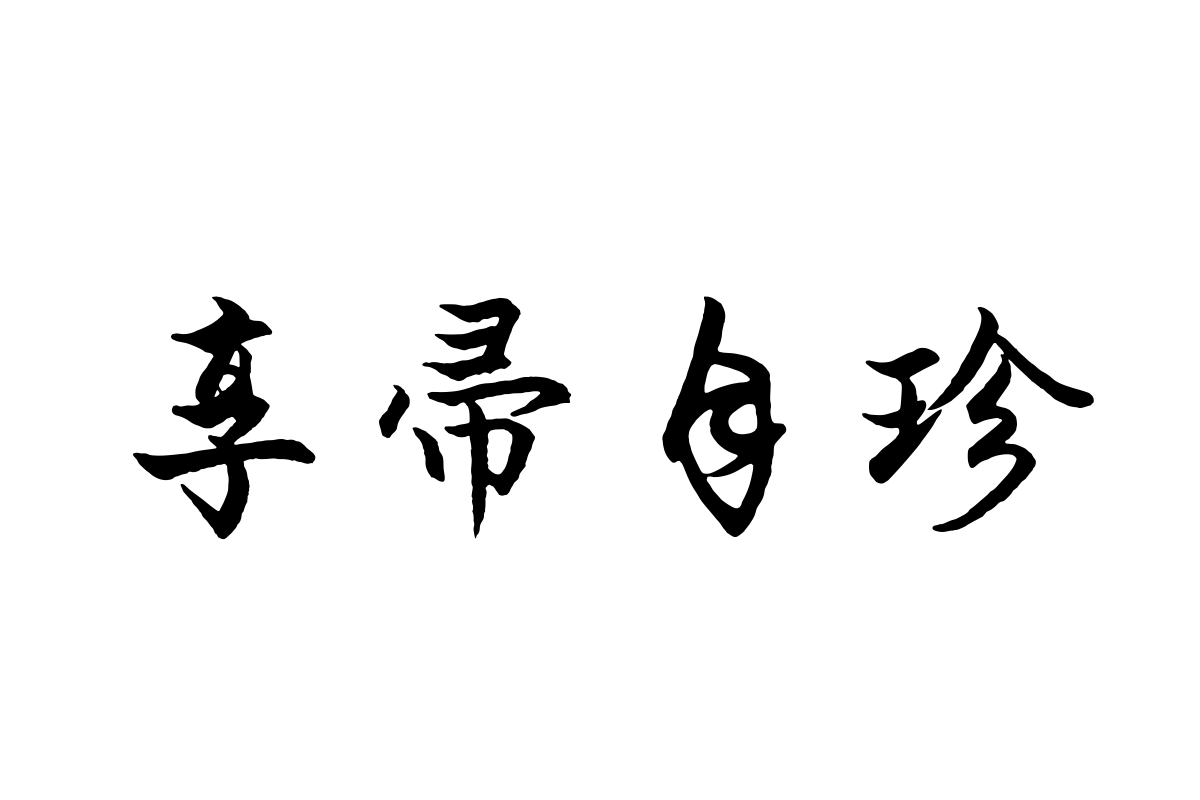
汉仪烟云繁字体是一套具有浓郁东方美感的中文字体,由汉仪字库公司设计。这套字体以其优美的线条和独特的字形结构而受到广泛好评。
汉仪烟云繁字体的特点包括:
1. 优雅流畅:该字体线条流畅,书写起来非常舒适,给人一种优雅的感觉。
2. 独特风格:每个字母都呈现出独特的形状和风格,使得整个字体既有传统韵味又不失现代感。
3. 易于识别:虽然笔画复杂,但整体结构清晰,易于识别和阅读。
4. 适用范围广:适用于各种文字设计领域,如书籍、杂志、广告、网页等。
总之,汉仪烟云繁字体是一款极具东方美感的中文字体,适合用于需要展现传统文化特色的场合。